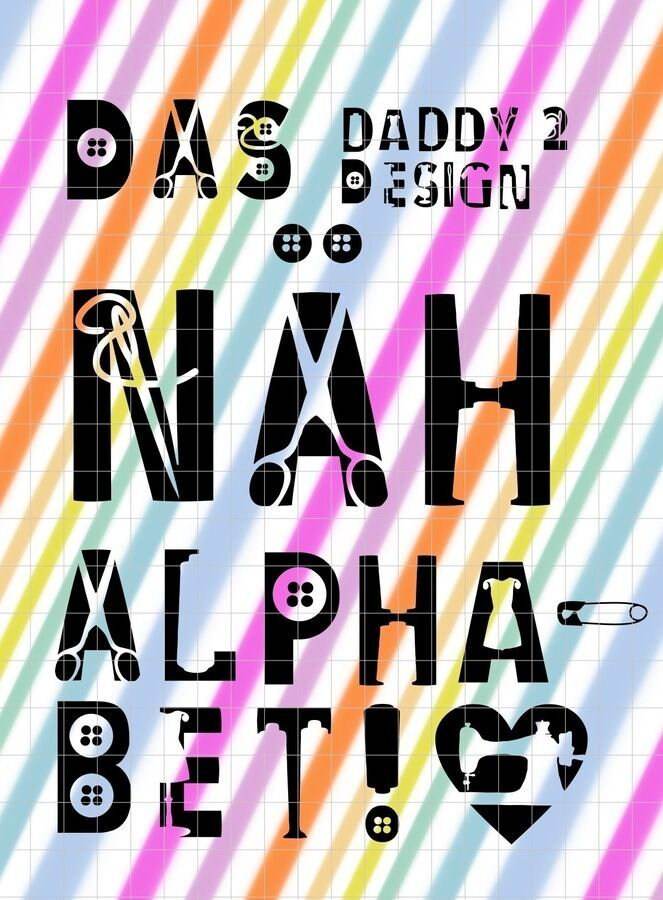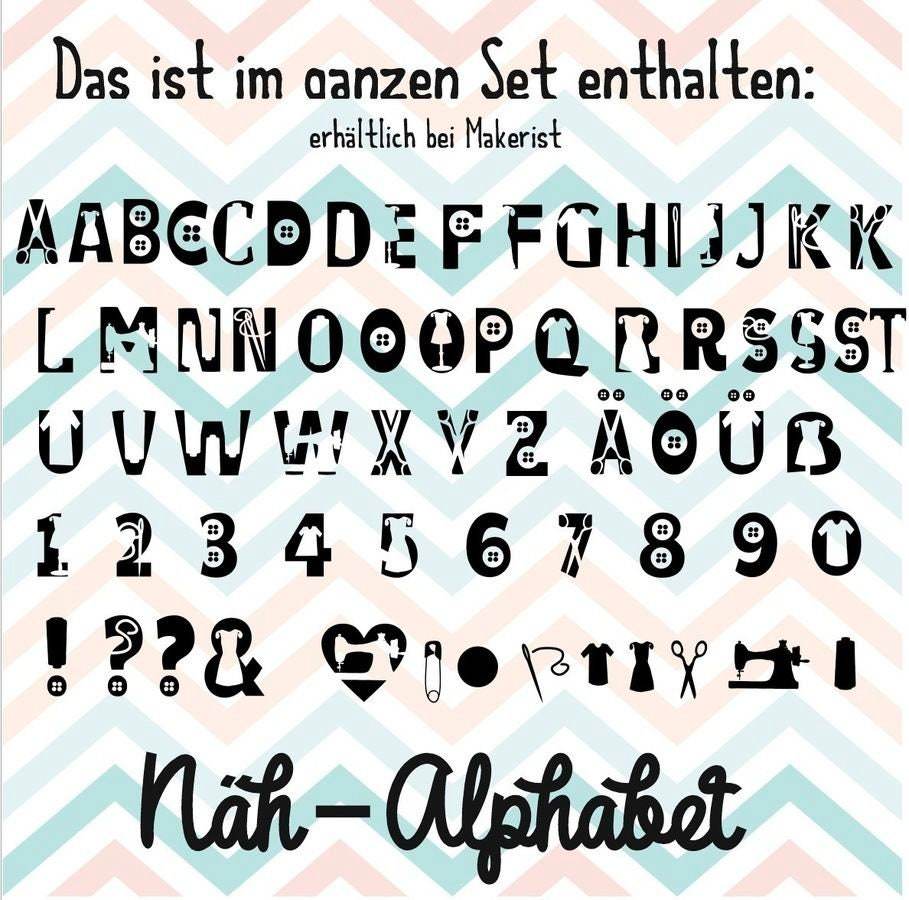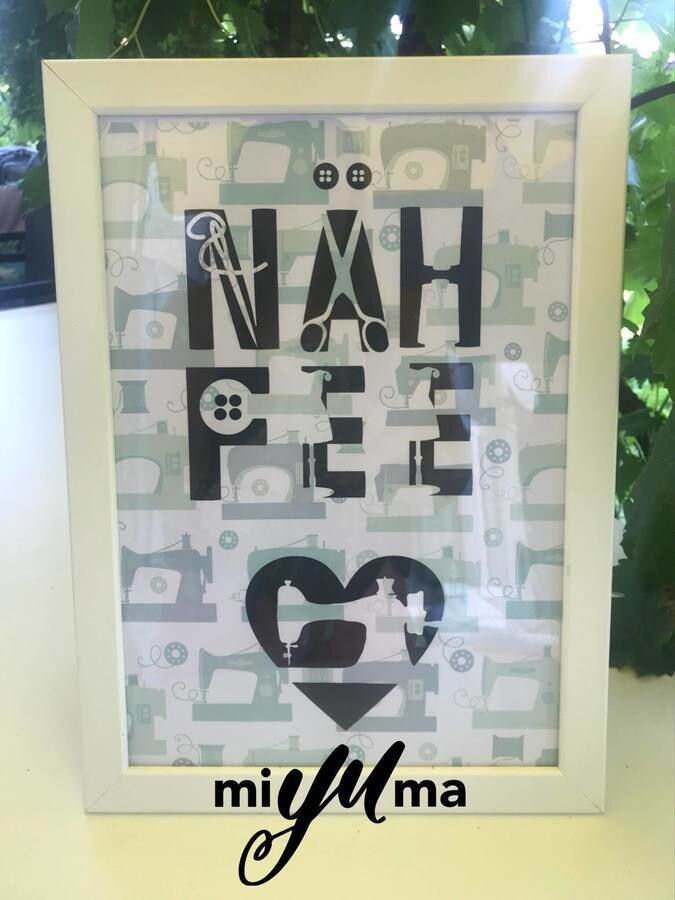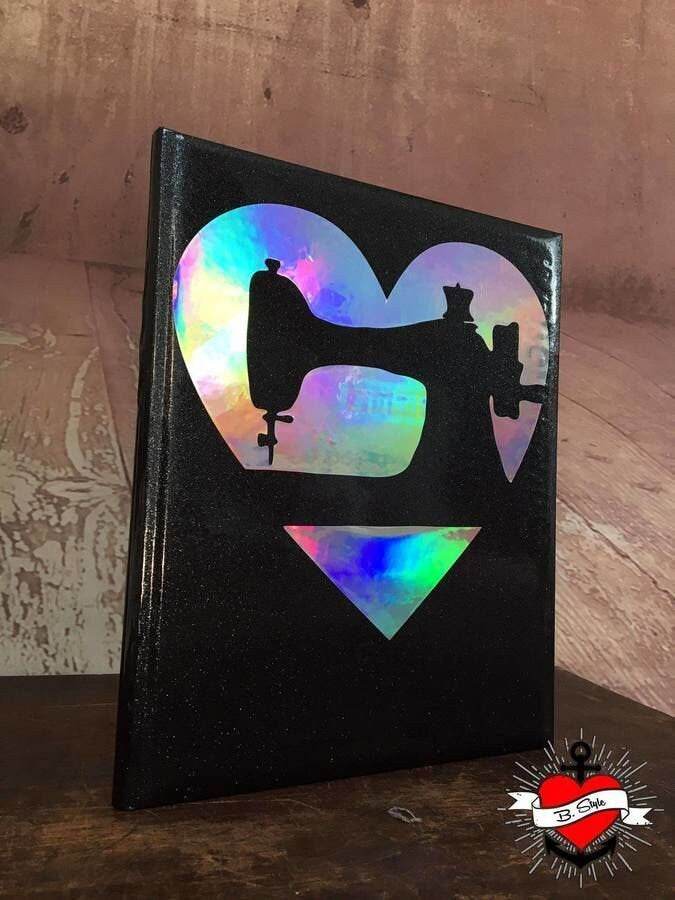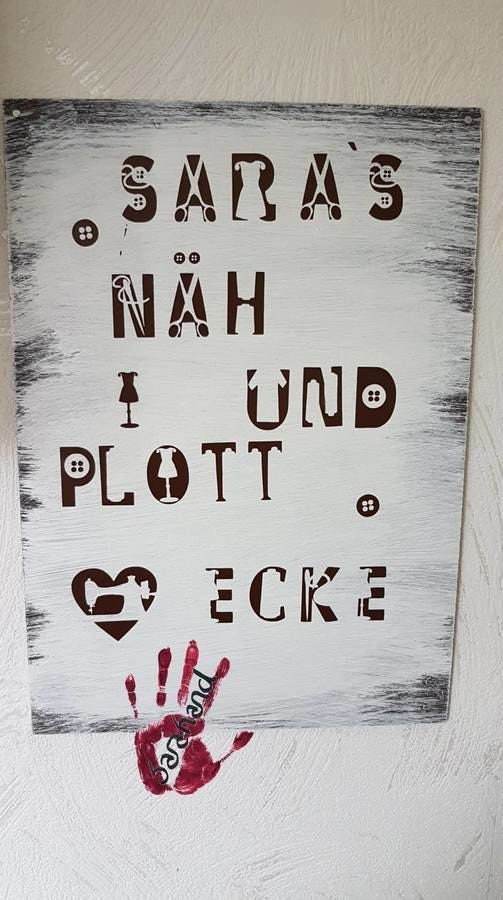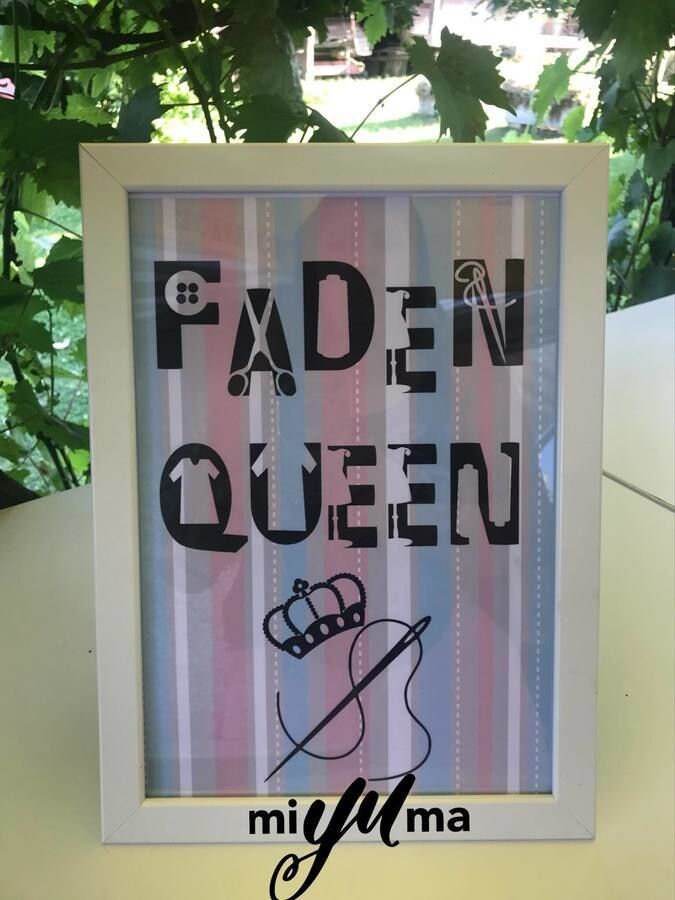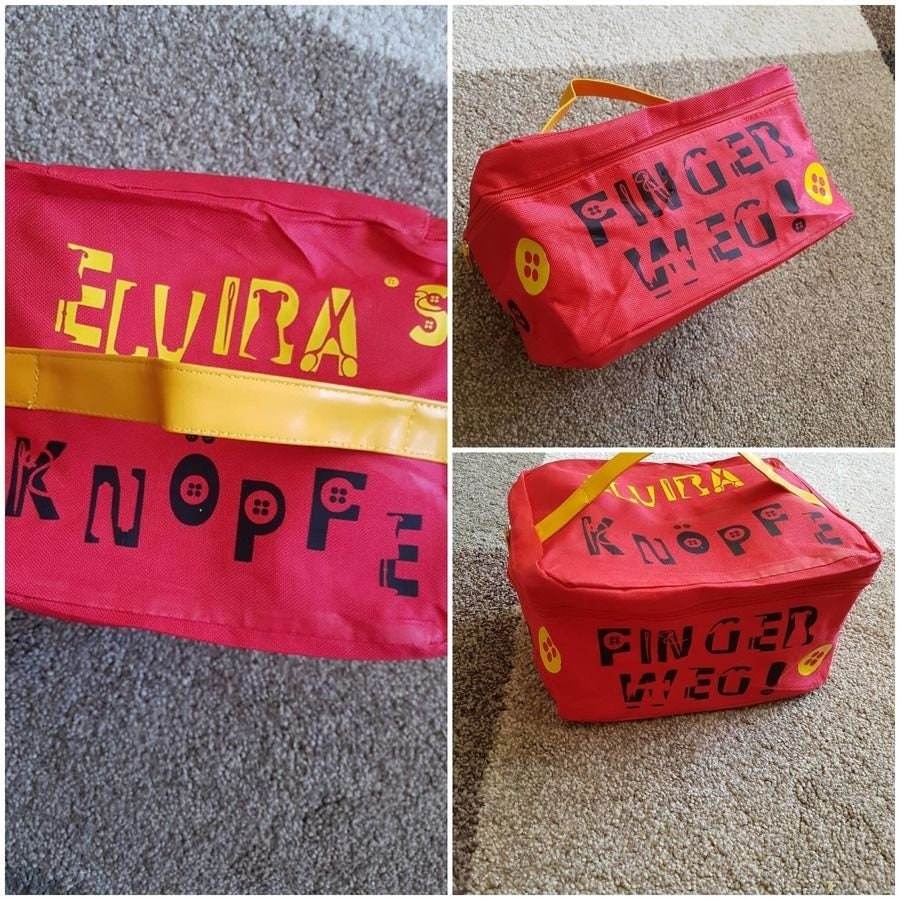
Das Näh-ALPHABET inklusive echter Schriftart und Plotter und Laser-Datei als SVG und DXF
Auf vielfachen Wunsch haben wir euch ein komplettes Shadow-Näh-Alphabet gemacht
Inkl. 30 Buchtstaben, Zahlen und Deko <3
Jetzt könnt ihr selbst eure Lieblings -Namen - Wörter und Sprüche zusammenstellen.